今日は、教室で作品に押すための新しいハンコを作ったので、そのお話をしますね。
書道の作品って、最後に名前の下に「落款」というハンコを押すことがあるんです。でも、うちの教室では生徒さん一人一人の名前入りハンコは用意できないので、市販のスタンプや私が彫ったハンコを使っています。
今回作ったハンコには、子どもたちが「よく書けた!」って感じられるような思いを込めました。ちょっと工夫をして、作品の仕上げがもっと楽しくなるものにしてみたんです。これから、そのハンコ作りの様子を写真とともにご紹介しますね!
作品仕上げに使うハンコとは?
書道の作品で、名前の下に押されている赤いハンコを見たことがありませんか?
あれは「落款(らっかん)」といって、作品の作者が自分の名前や雅号(がごう:書道での名前)を入れるためのハンコなんです。書道ではこの落款を押すことで、作品が完成したことを示します。
でも、もじもじでは少し違うスタイルでハンコを押しています。生徒さん一人一人の名前のハンコを作るのは難しいので、代わりに「教室のハンコ」や市販されているスタンプを使っています。作品が仕上がったときに、ハンコを押すとなんだか特別感が出て、子どもたちも達成感を感じられるみたいです♪
今回の新しいハンコは、もっとその仕上げが楽しくなるようなものを目指しました!
子どもたちの声をを新しいハンコに!
今回のハンコは、「よく書けた!」という仕上げた時の子どもたちの声をそのまま表現してみました。
これまでは、市販のスタンプを使って作品を仕上げていましたが、教室オリジナルの子どもの思いを表現したハンコがあったらもっと楽しいかなと思ったんです。それで、筆の絵を入れたデザインで作ってみました。
このハンコのように、子どもたちが自分の作品に対して「書けた!」と自信を持ってくれるといいなと思っています。
ハンコができるまで
では、ここからは新しいハンコができるまでの様子をお見せしますね!
まずは石の素材選びからスタート。選んだ石を耐水ペーパーでやすりにかけ、整えます。トレーシングペーパーにデザインを描きます。
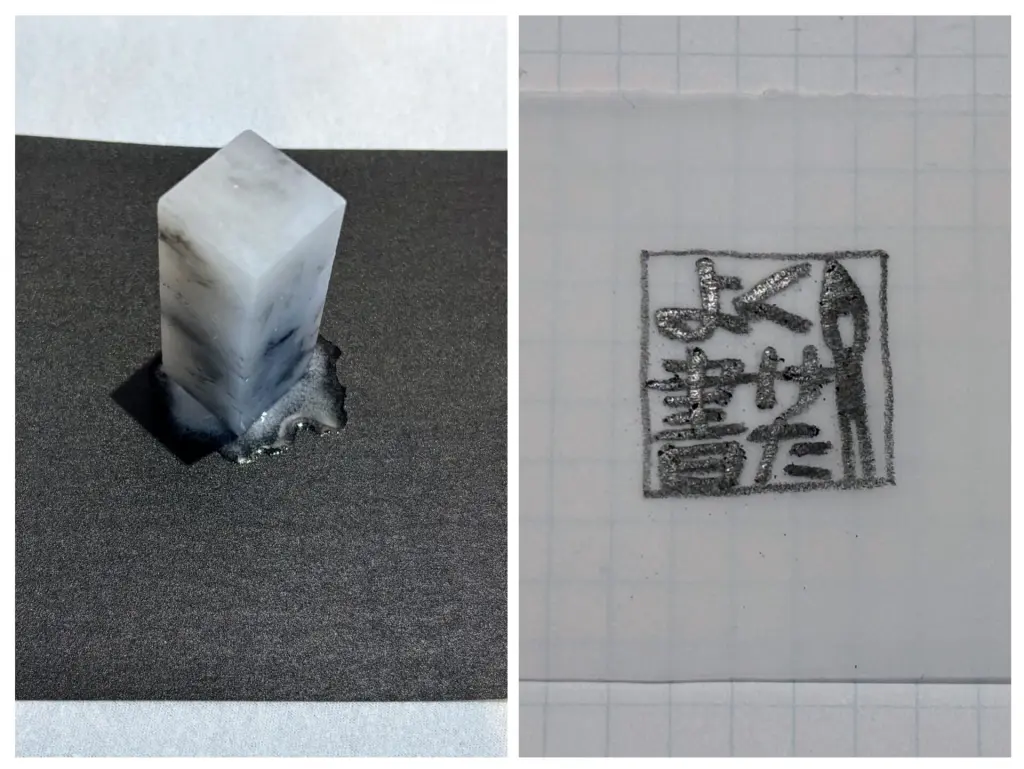
次は考えたデザインを石に転写します。石の表面にインクを塗り、その上からトレーシングペーパーをのせ、強く擦ります。
油性マジックで転写したデザインをなぞり、彫っていきます。彫る作業は細かくて集中力が必要ですが、少しずつ形が見えてくると楽しいんです。
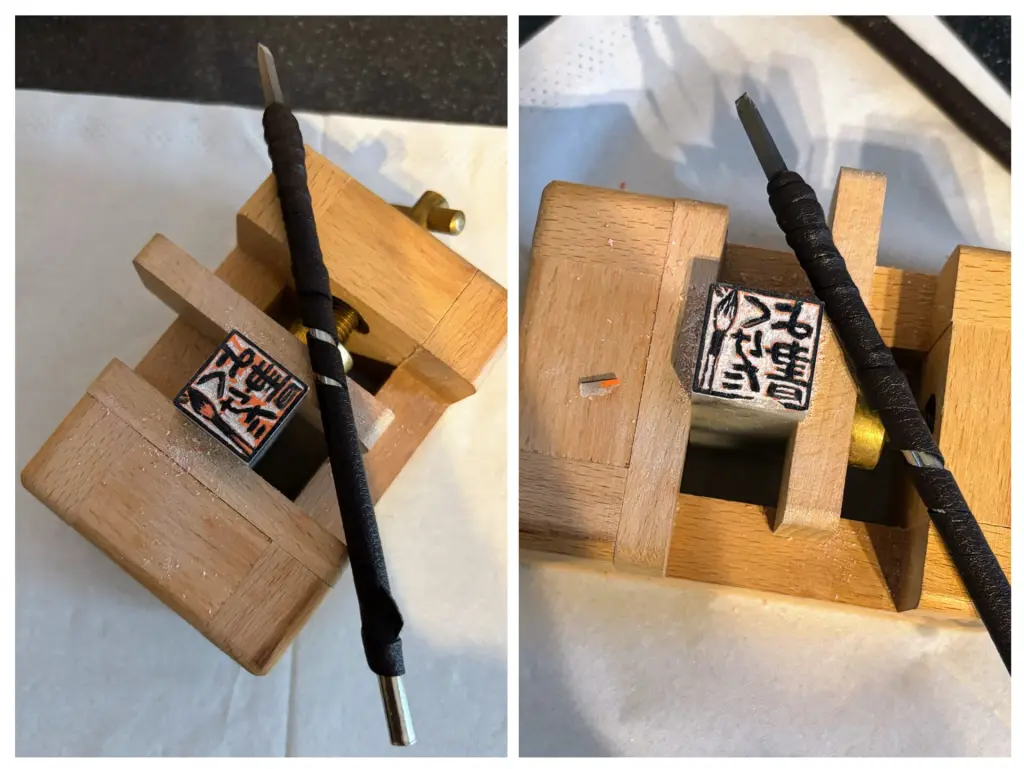
石の左側面に筆の絵を彫って完成です。左側面に印を入れるのは、ハンコを押すときに上下逆さまにならないように。左側の見える位置に印がくるようにして押印します。細かい作業ですが、完成までワクワクしながら進めました!(柔らかい石なので、彫っている最中に「書」の下が欠けてしまいました)
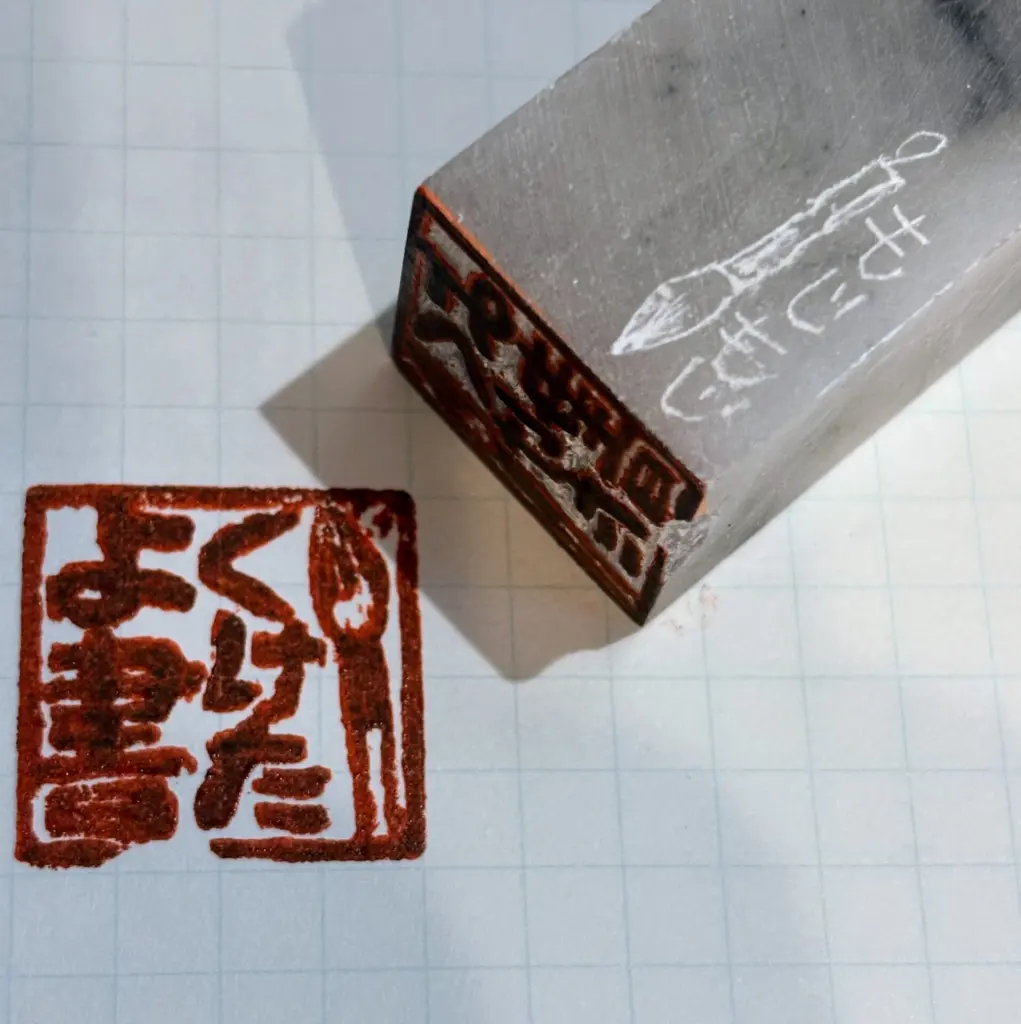
新しいハンコを見せてクイズタイム!
新しいハンコが完成したので、生徒たちにさっそく見せてみました!
ただ、ハンコって押してみると鏡文字になるんですよね。そこで、教室が始まったときにちょっとしたクイズを出してみました。「さて、このハンコには何て書いてあるでしょう?」と問いかけると、生徒たちは「うーん、なんだろう?」と真剣に考え始めました。
実際に押してみないとわからないことに気づいた子もいれば、ヒントを頼りに正解を当てた子もいて、教室はちょっとしたクイズ大会みたいな雰囲気に♪ みんな楽しんでくれたようで、「またこういうクイズやって!」なんて声も聞こえてきました。
次は作品の仕上げにこのハンコを押して、もっと楽しく作品作りを進めていけたらいいなと思っています!